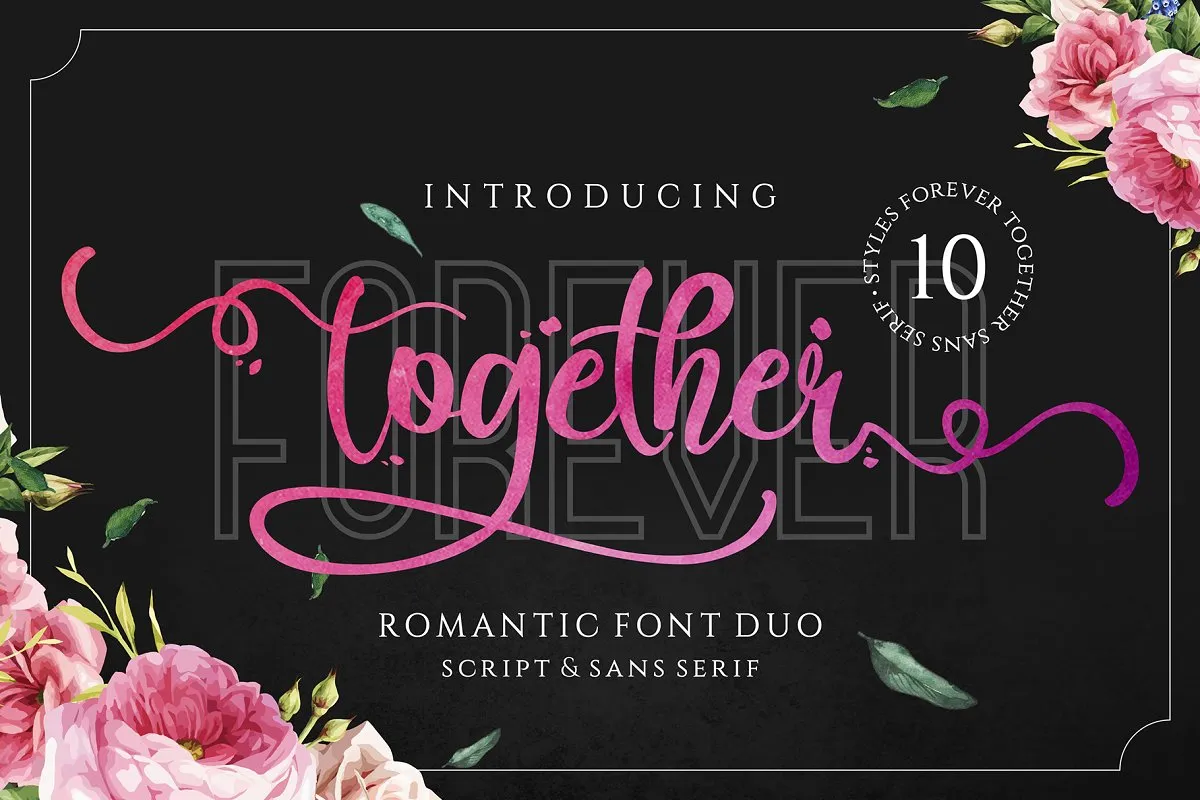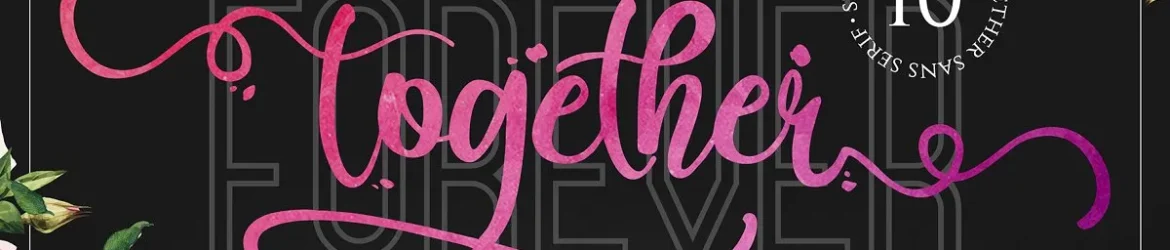
Forever Together Romantic Font Duo – Download Grátis
Hello guys! Há uma nova família de serif falsa moderna e comprimida para compartilhar com vocês hoje. Introduzimos a Forever Together Sans Font Family de Hamilton, uma nova criação da Aliseo Font Family, que é um forte e limpo modelo de serif falsa. Esta fonte vem equipada com versatilidade para trabalhos em estilos tradicionais e fortes. Aliseo está perfeitamente adaptável a qualquer tipo de trabalho, como logotipos, magazines, vídeos, embalagens de produtos, cabeçalhos de websites, designs de roupas e muito mais. Sem dúvida, é uma fonte que não pode ser esquecida para qualquer aplicação gráfica moderna.